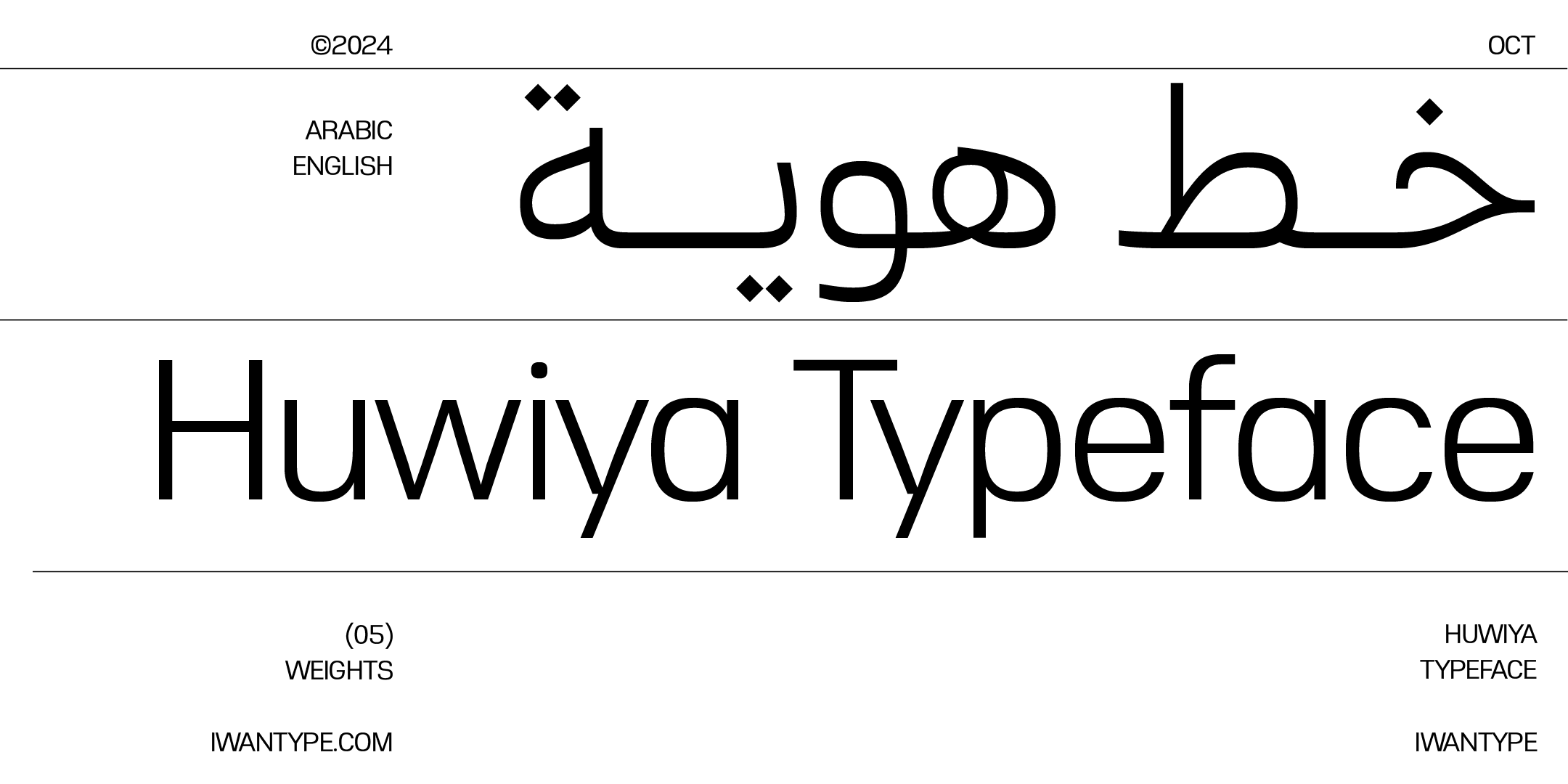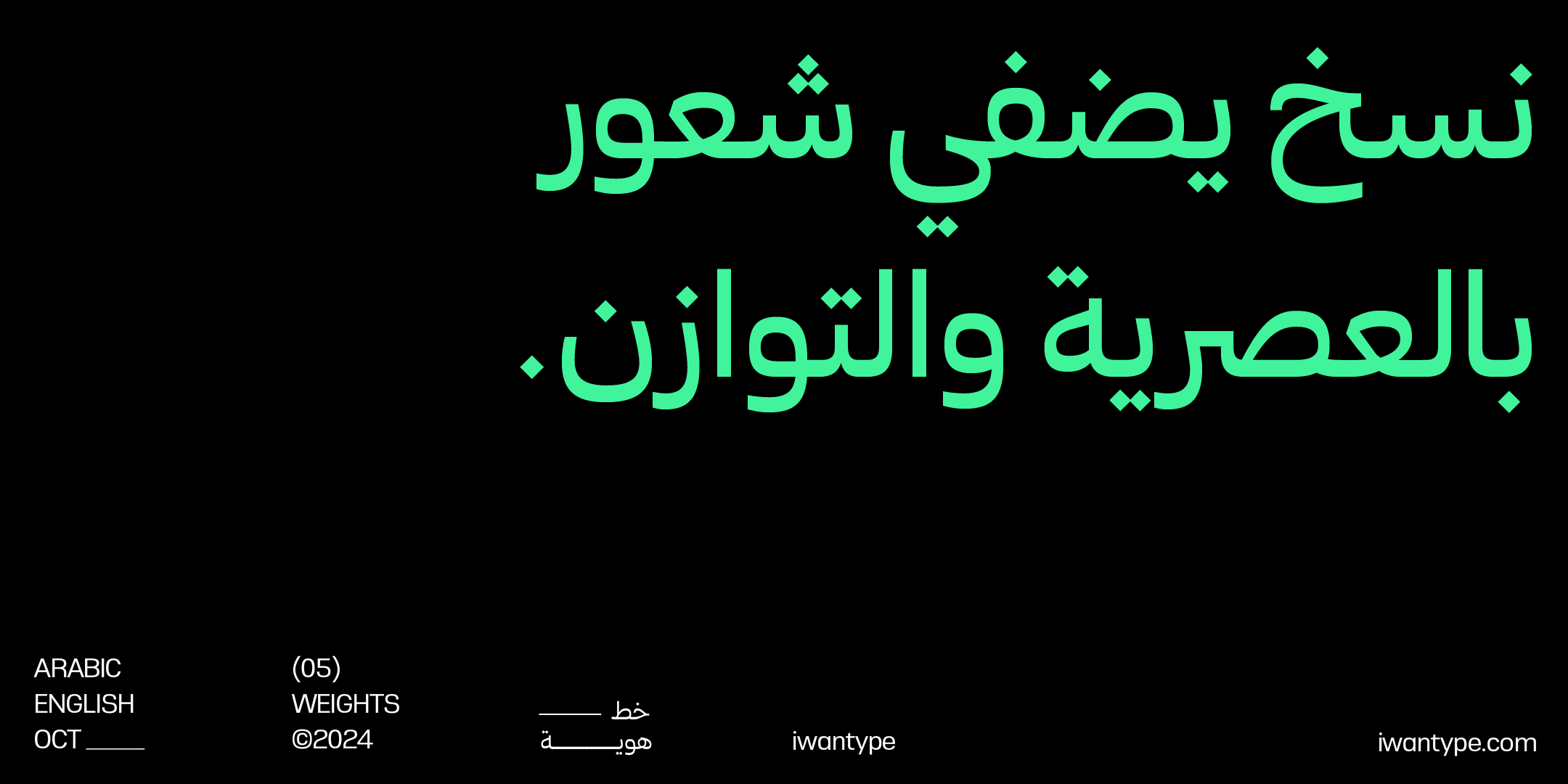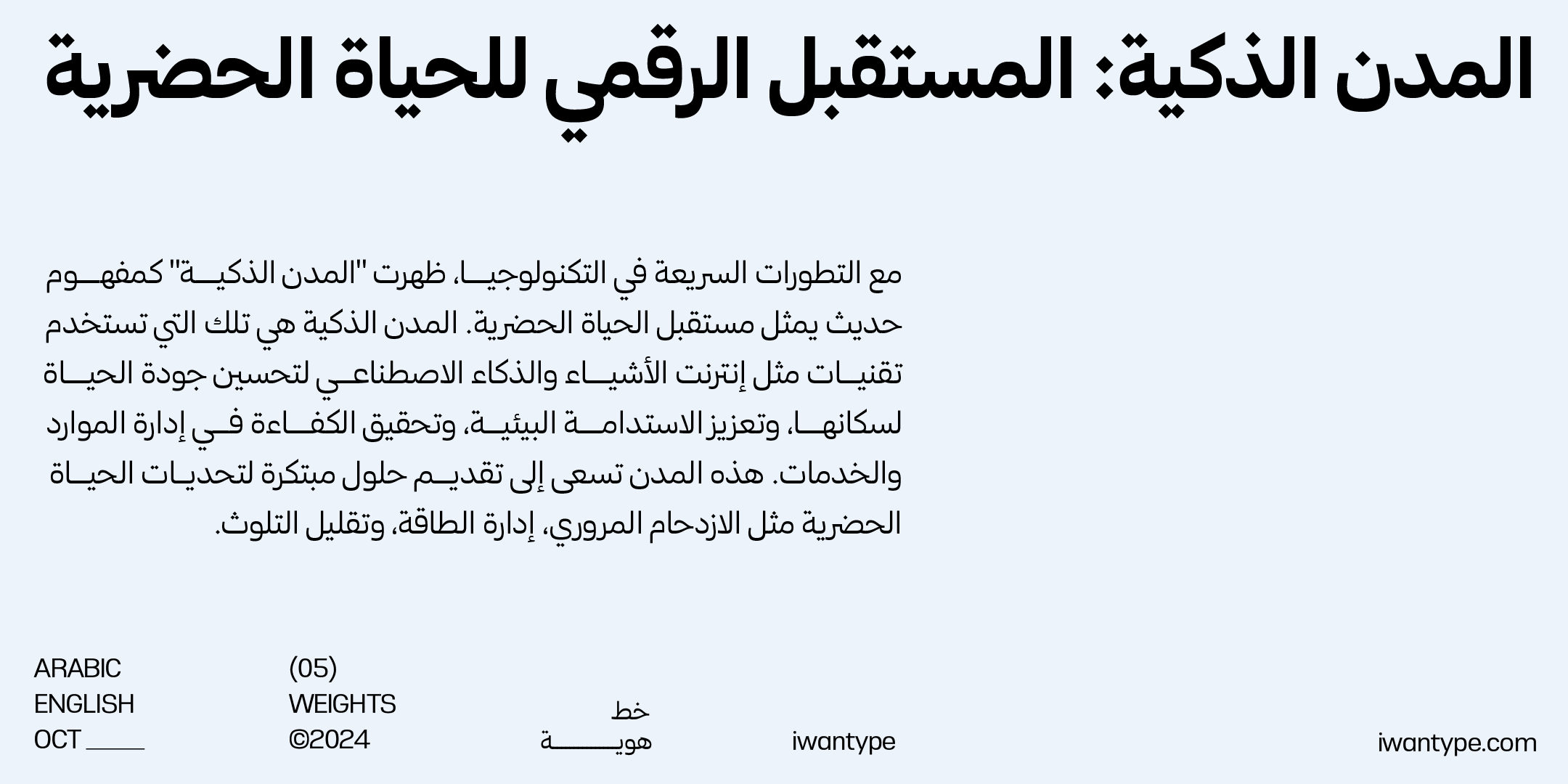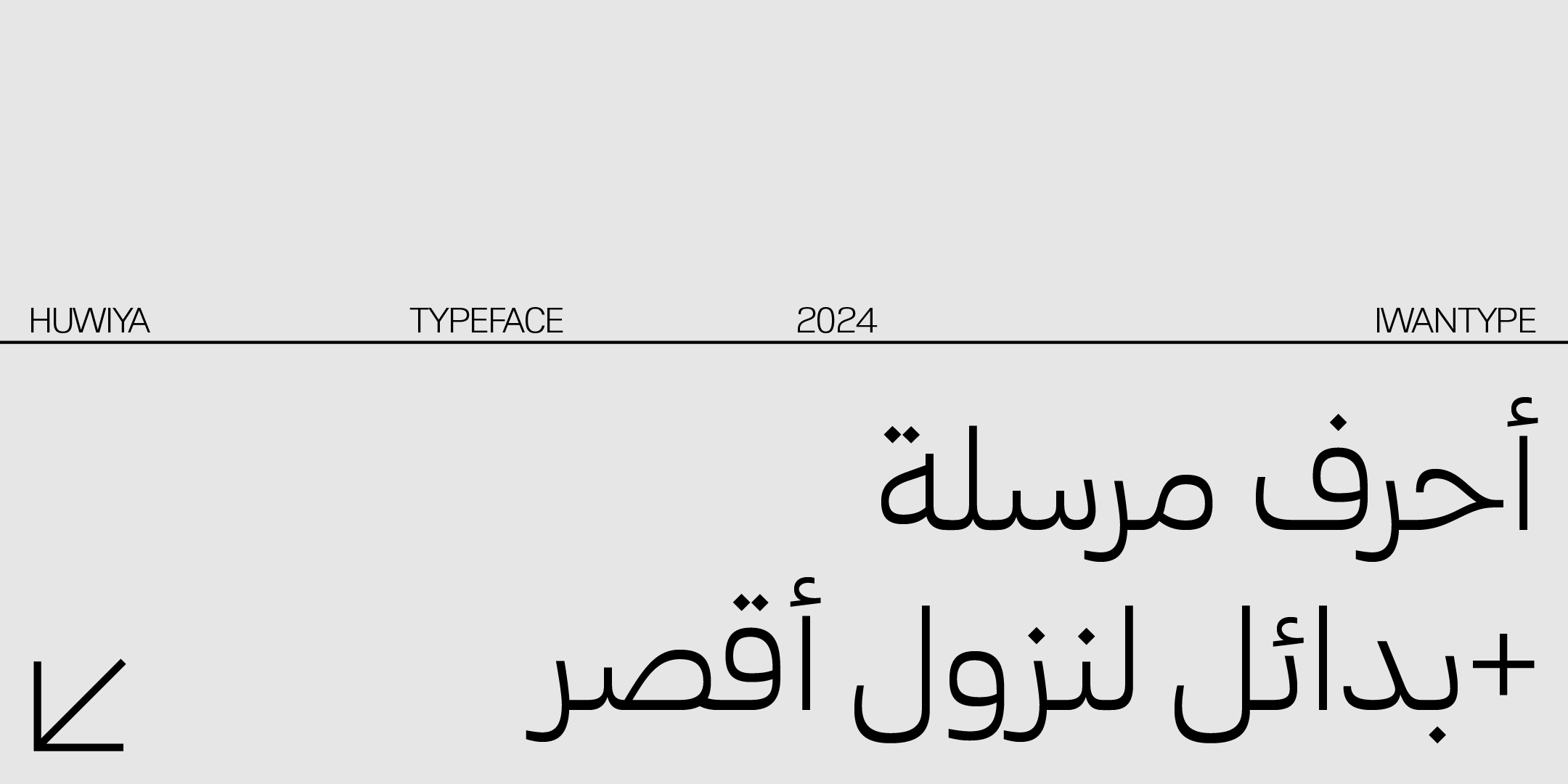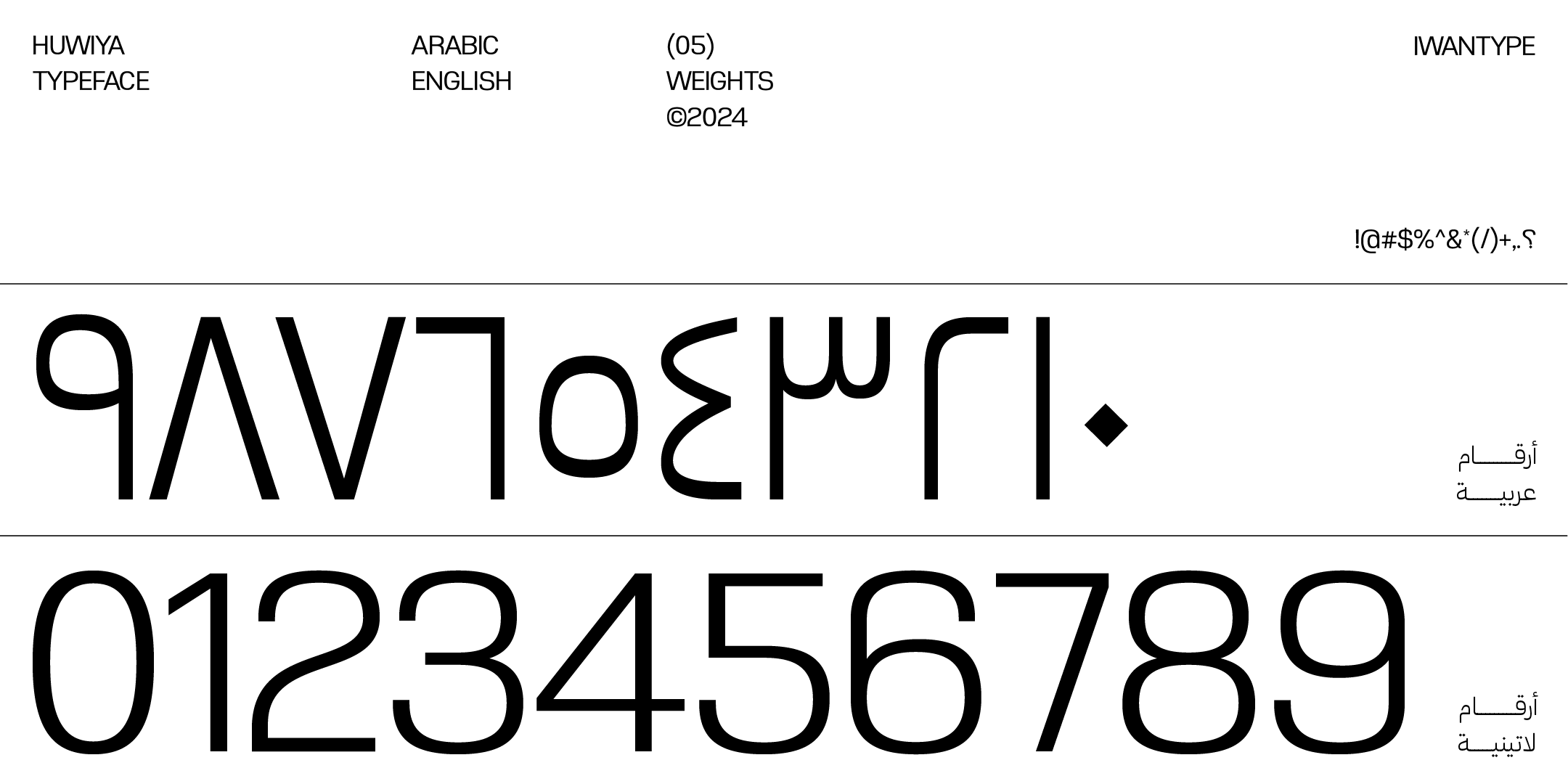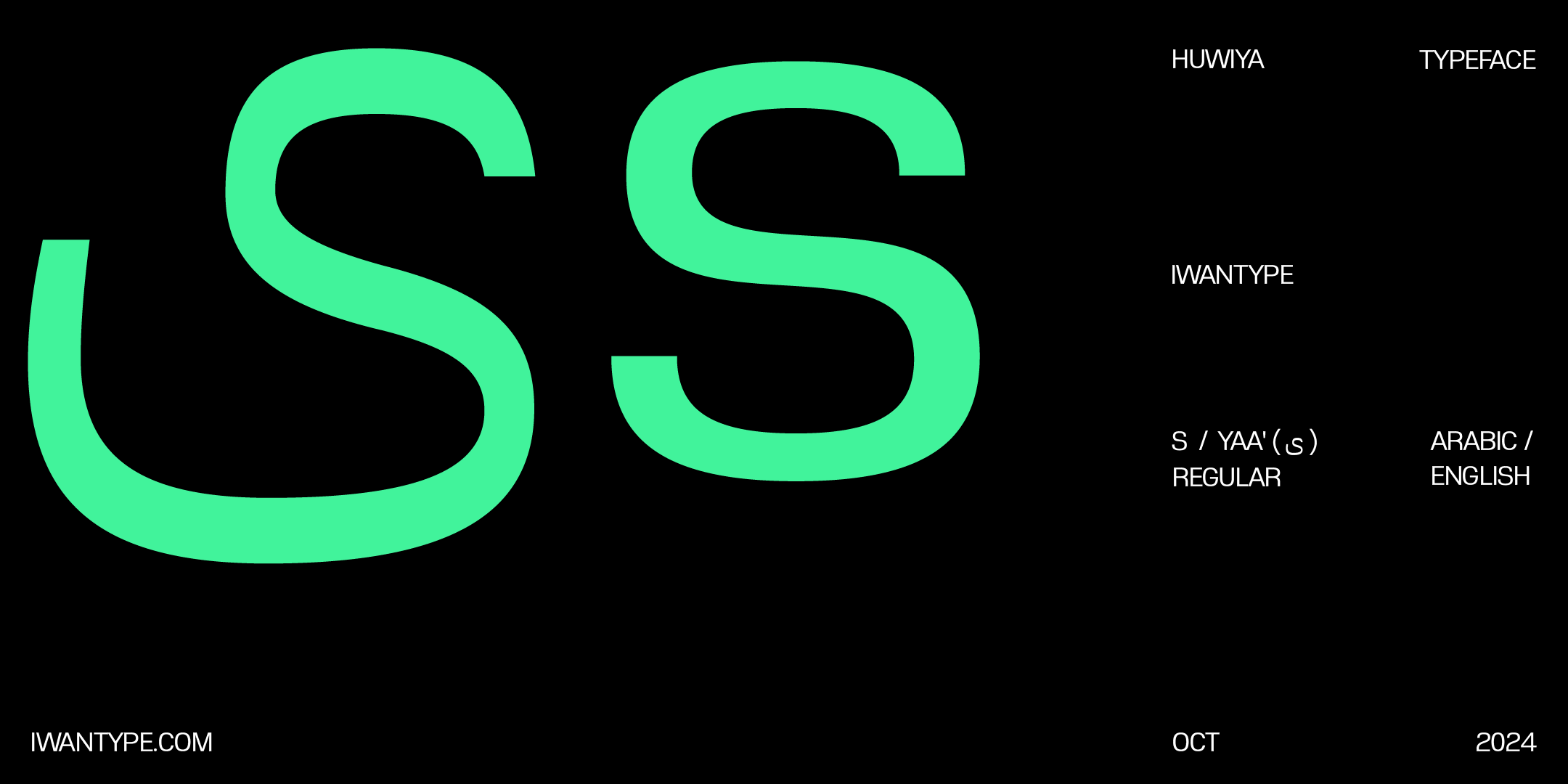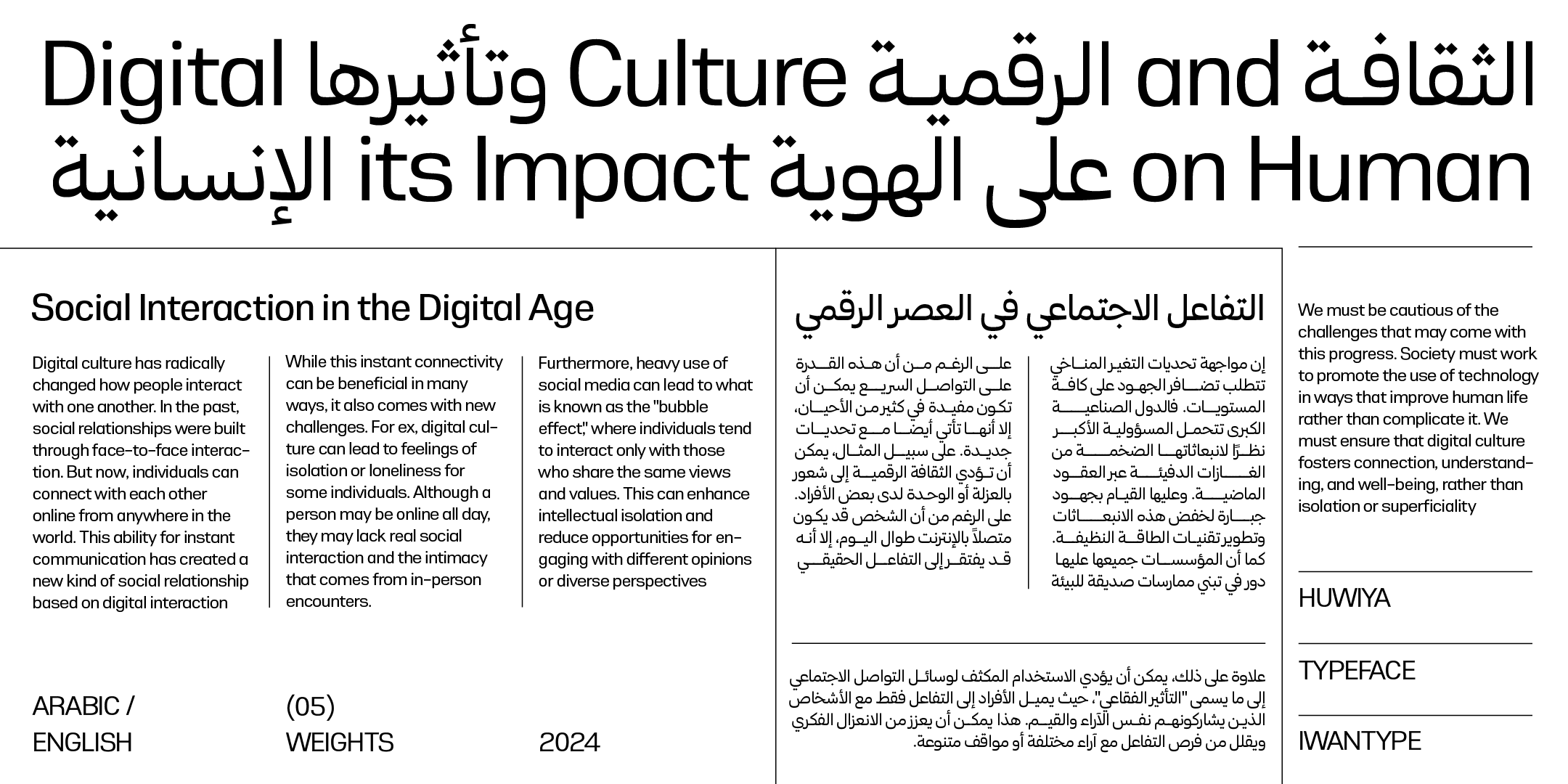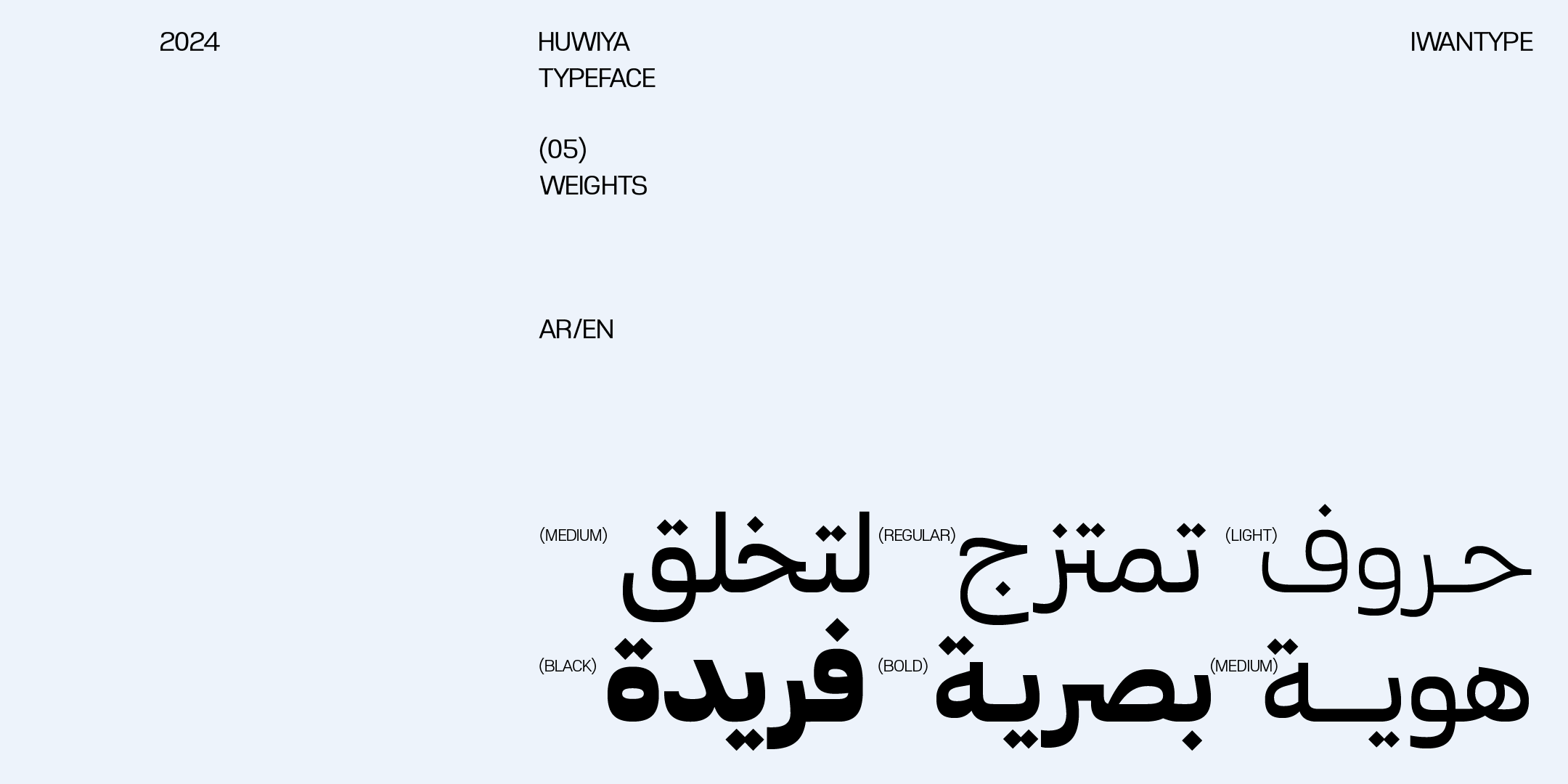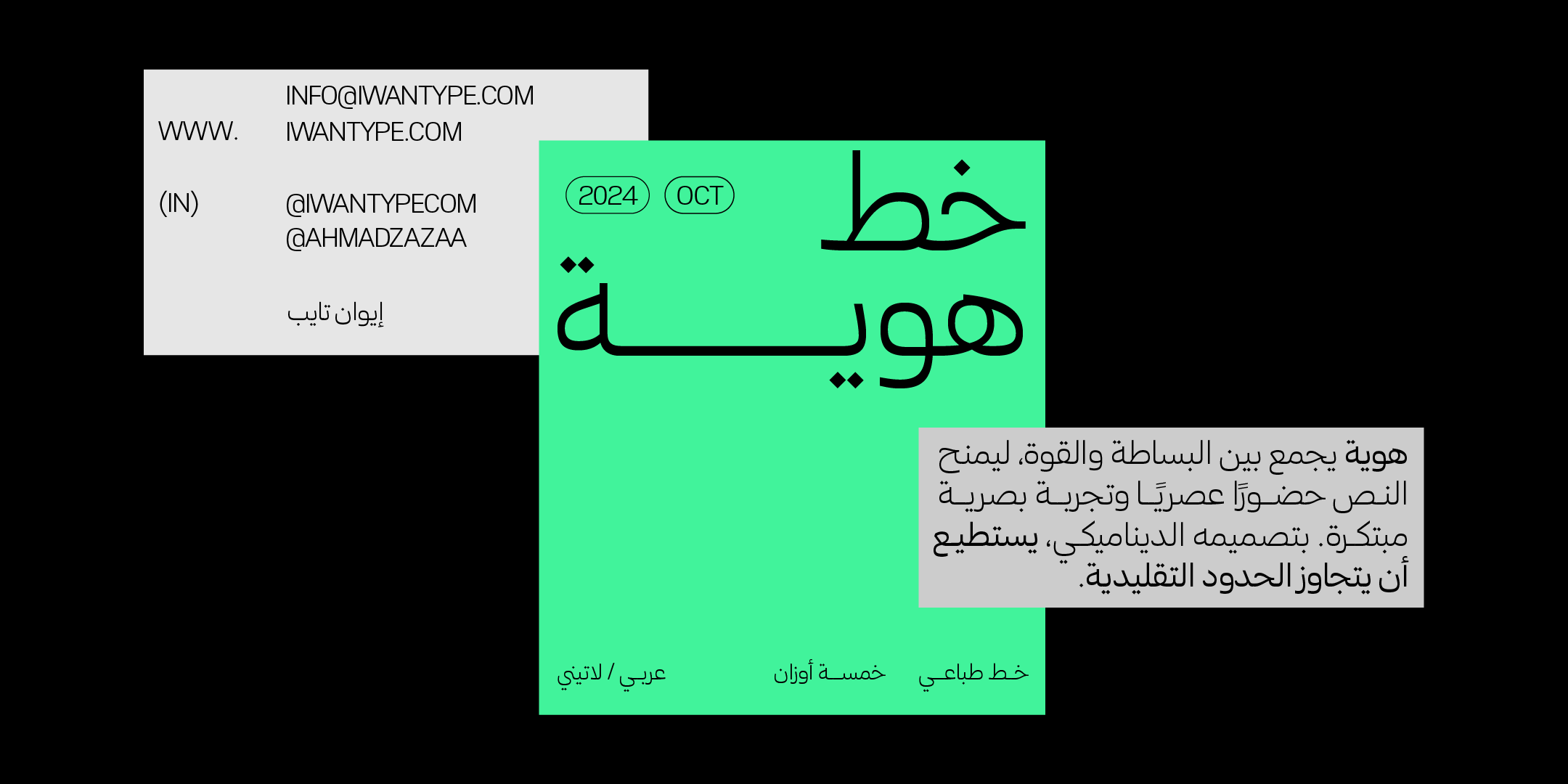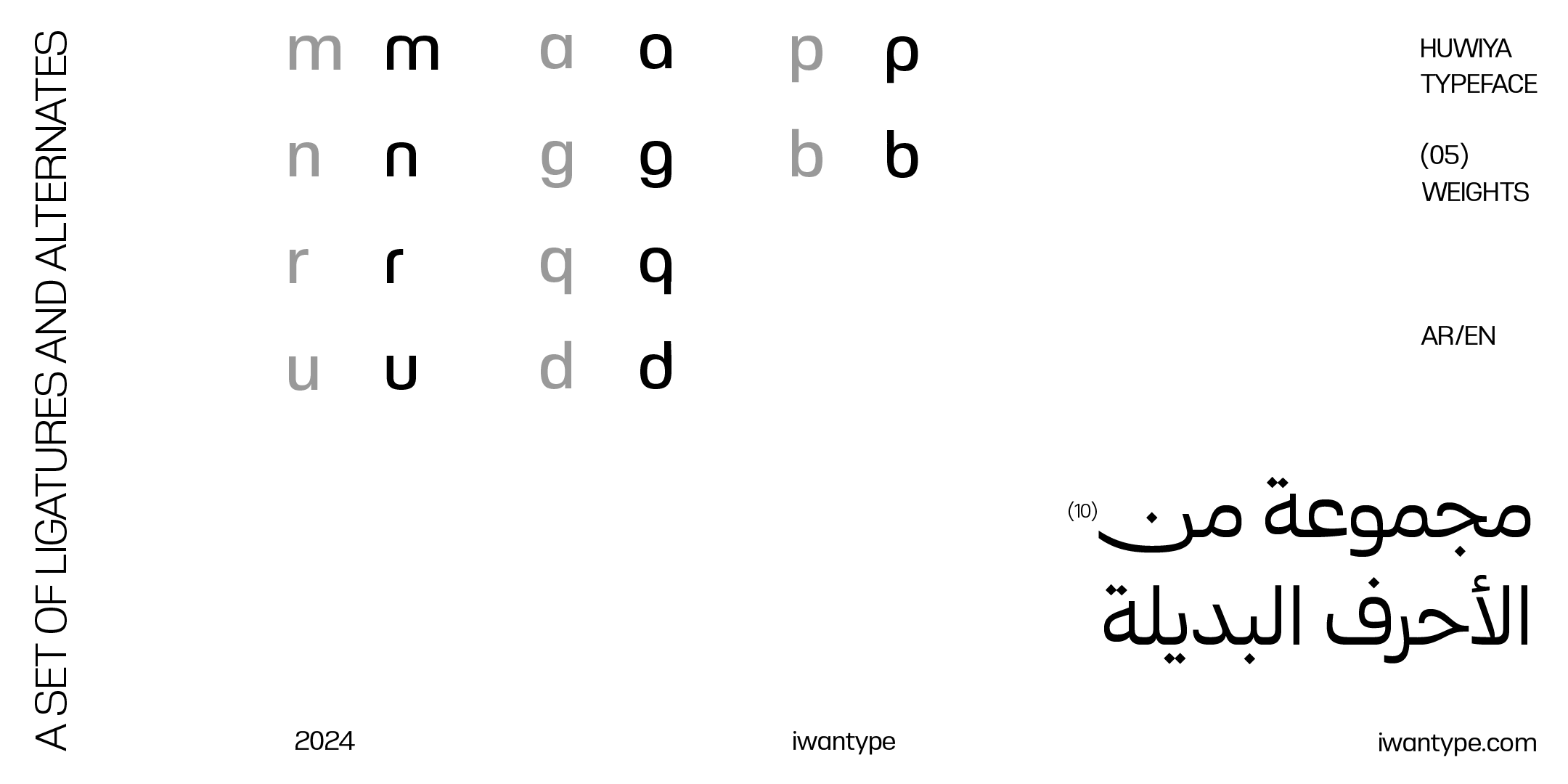
خط هوية الطباعي – خط نسخ – Huwiya Arabic typeface
خط هوية الطباعي الجديد من Iwantype هو تجسيد للتوازن بين الحداثة والبساطة. يتميز الخط بتصميمه يجمع بين الزوايا القائمة والحواف الدائرية، ما يمنحه طابعًا عصريًا وواضحًا. يتوفر الخط بخمسة أوزان مختلفة (رفيع، عادي، متوسط، سميك، وأسود)، مما يتيح مرونة عالية في الاستخدام لتطبيقات متعددة، سواء في الطباعة أو العرض الرقمي.هوية هو خط متعدد اللغات (يدعم العربية والإنجليزية)، ما يجعله خيارًا مناسب لمشاريع التصميم التي تتطلب تكاملًا سلسًا بين اللغتين. تم تصميمه ليتناسب مع الشعارات، العناوين، والنصوص، مما يجعله مثاليًا للاستخدام في الهويات البصرية، الحملات الإعلانية، والعروض التقديمية.
مميزات خط هوية الطباعي:
- مزايـا OpenType: يتضمن الخط العديد من مزايا OpenType التي تضفي عليه مرونة وتنوعًا في الاستخدام، مثل:
- الحروف المرسلة: لمسة تقليدية تضفي على النصوص جمالية خاصة.
- حرف ياء بنزول أقل: يقلل من نزول السطر، مما يعزز من انتظام النصوص.
- النقطة الدائرية البديلة: توفر تنوعًا وجاذبية بصرية إضافية للنصوص.
- الحروف المركبة: تسهم في تحسين المظهر العام للنص وتزيد من سلاسته.
- توافر الأوزان: يأتي خط هوية الطباعي بخمسة أوزان مختلفة.
اللغات : العربية والإنجليزية